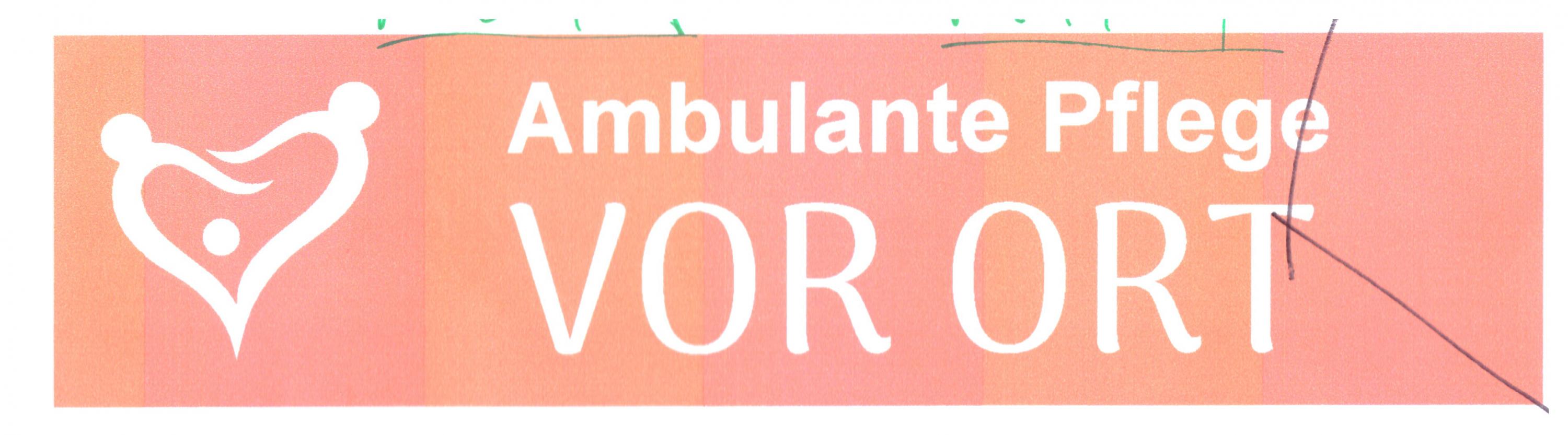
Verzweifelte Suche nach DIESER (HAND)SCHRIFT
Ich benötige den Namen der unteren Schriftfamilie.
Es liegt mir auf der Zunge komm aber nicht drauf.
Das könnte die Cronos sein. Muss ich direkt mal nachschauen …
Nachtrag: Hm, nee, diese Schrift ist geschwungener als die Cronos.
Das könnte die Cronos sein.
Eine ähnliche Anmutung hätten außerdem die:
• Maiandra
• Overlock
• Fontin
• FS Pimlico
• Capucine
• Congenial
• Palatino Sans